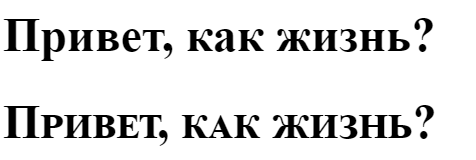
Шрифты
Компьютерный шрифт
Файл шрифта — это файл, содержащий в себе набор символов
и соответствующих им кодов.
Символы могут быть различными по назначению:
Aa
языковые знаки
07
цифровые
☂⁂
графические
$#!
специальные
Вывод шрифтов
Растровые
Векторные
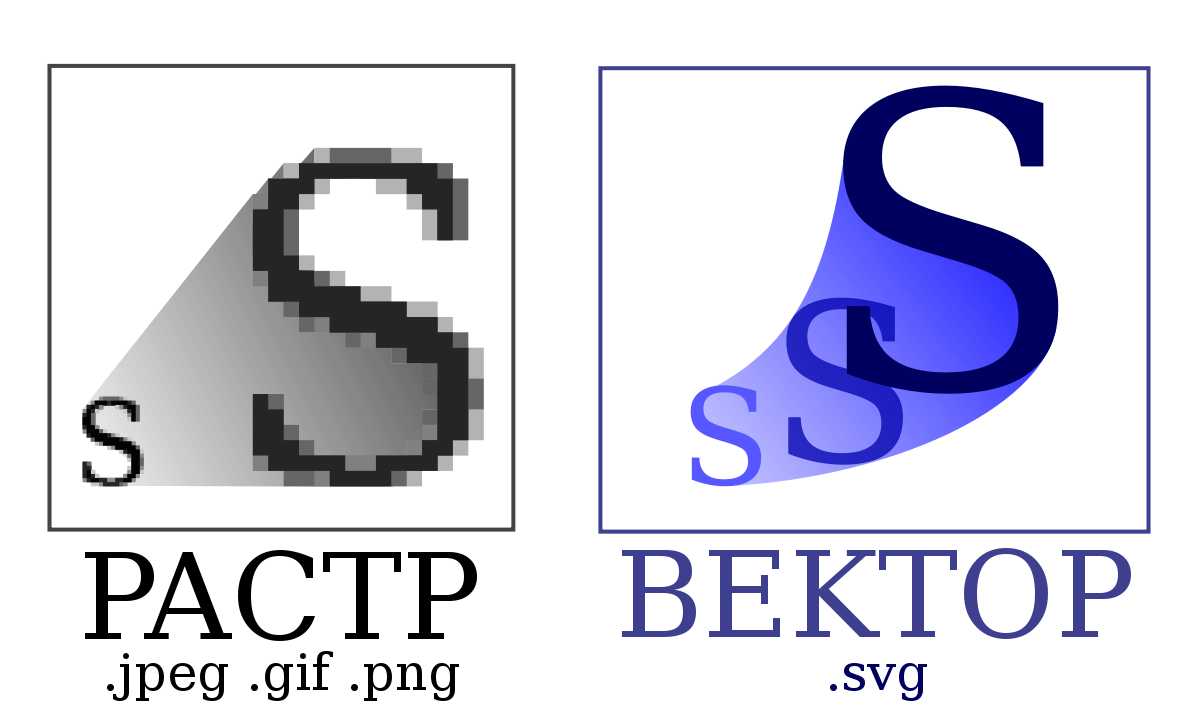
Растровые шрифты
Были распространены в эпоху матричных принтеров и экранов с низким разрешением и представляли собой набор растровых изображений каждого символа в виде битмапа.
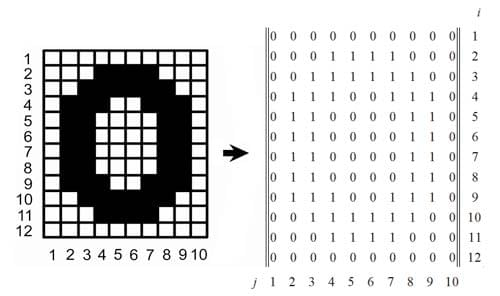
Векторные шрифты
Векторная графика основана на математических формулах геометрических объектов.
Современные шрифты описывают символы с помощью тех самых формул, что позволяет их масштабировать без потери качества, как и любое другое векторное изображение.
Анатомия шрифта
Baseline
Базовая линия — воображаемая прямая линия, проходящая по нижнему краю прямых знаков без учёта свисаний и нижних выносных элементов.
- Высота прописных знаков — расстояние от базовой линии до верхней линии прописных, то есть высота прописных букв без учета свисаний.
- Высота строчных знаков — расстояние от базовой линии до верхней линии строчных, то есть высота строчных букв без свисаний и выносных элементов.
Высота строки — расстояние между базовыми линиями строк.
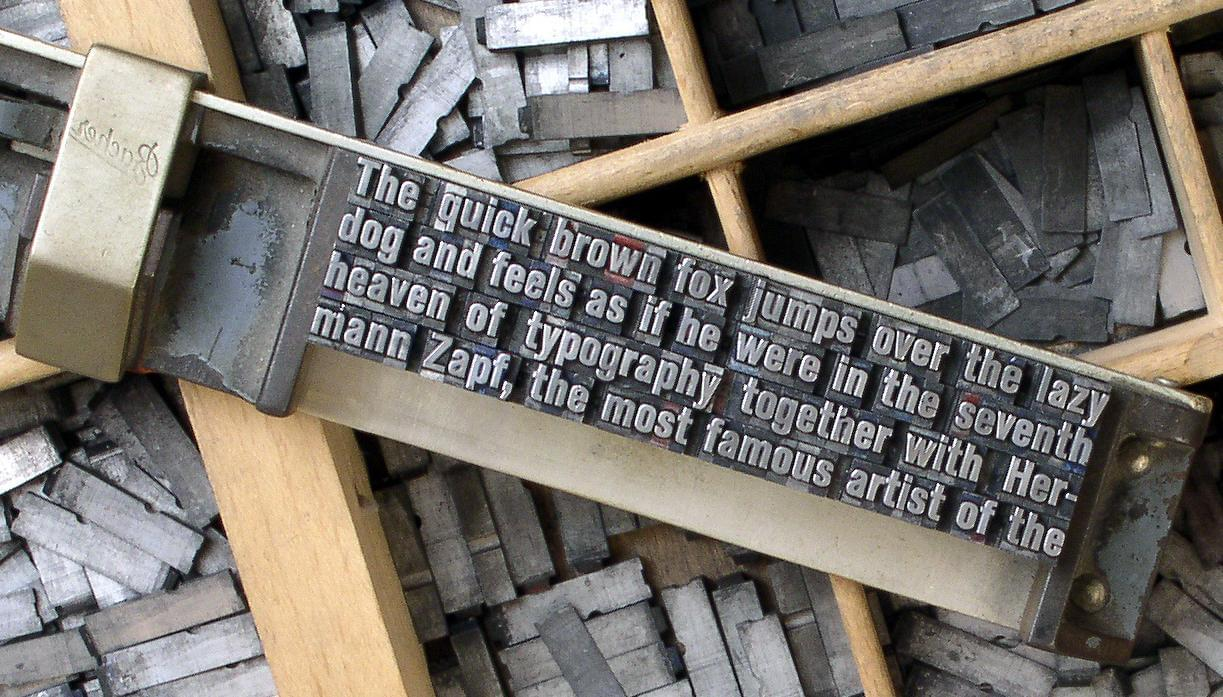
Кегельная площадка — верхняя прямоугольная часть ножки литеры, на которой расположено выпуклое (печатающее) изображение знака.
В цифровом шрифте кегельная площадка важна при проектировании шрифта как прямоугольник, в который вписывается изображение знака.
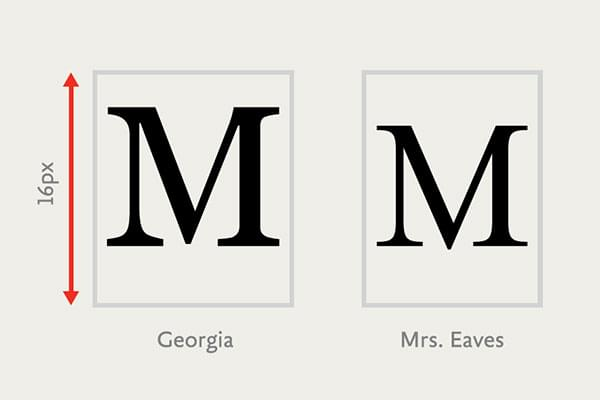
Гарниту́ра в типографике — набор из одного или нескольких шрифтов в одном или нескольких размерах и начертаниях, имеющих стилевое единство рисунка и состоящих из определённого набора типографских знаков.
Размер шрифта
Размер шрифта можно установить с помощью
единиц измерения длины.
С помощью font-size можно определить размер шрифта элемента. Размер шрифта определяется как высота от базовой линии до верхней границы кегельной площадки.
Единицы измерения длины
px — размер шрифта в пикселях.
Так как задание динамического размера требуется нечасто, эта единица измерения является наиболее популярной.
}em или % — размер шрифта в зависимости от размера шрифта родителя. Эти размеры – относительные, они определяются по текущему контексту.
rem(root em) — подобно em наследует значение, но только <html>.
Расстояние между буквами
Для изменения данного расстояния предусмотрено
свойство letter-spacing со значением в любой
единице измерения длины, кроме процентов.
Высота строки
line-height - Высота строки. Устанавливается двумя типами значений: единицами измерения длины или безразмерным множителем.
Расстояние между словами
Для изменения данного расстояния предусмотрено
свойство word-spacing со значением в любой
единице измерения длины, кроме процентов.
Гарниту́ра в типографике — набор из одного или нескольких шрифтов в одном или нескольких размерах и начертаниях, имеющих стилевое единство рисунка и состоящих из определённого набора типографских знаков.
Характеристики рисунка одной гарнитуры:
Наклон
Насыщенность
Плотность
- Начинает загрузку шрифта
- По окончанию загрузки парсит шрифт и применяет к странице
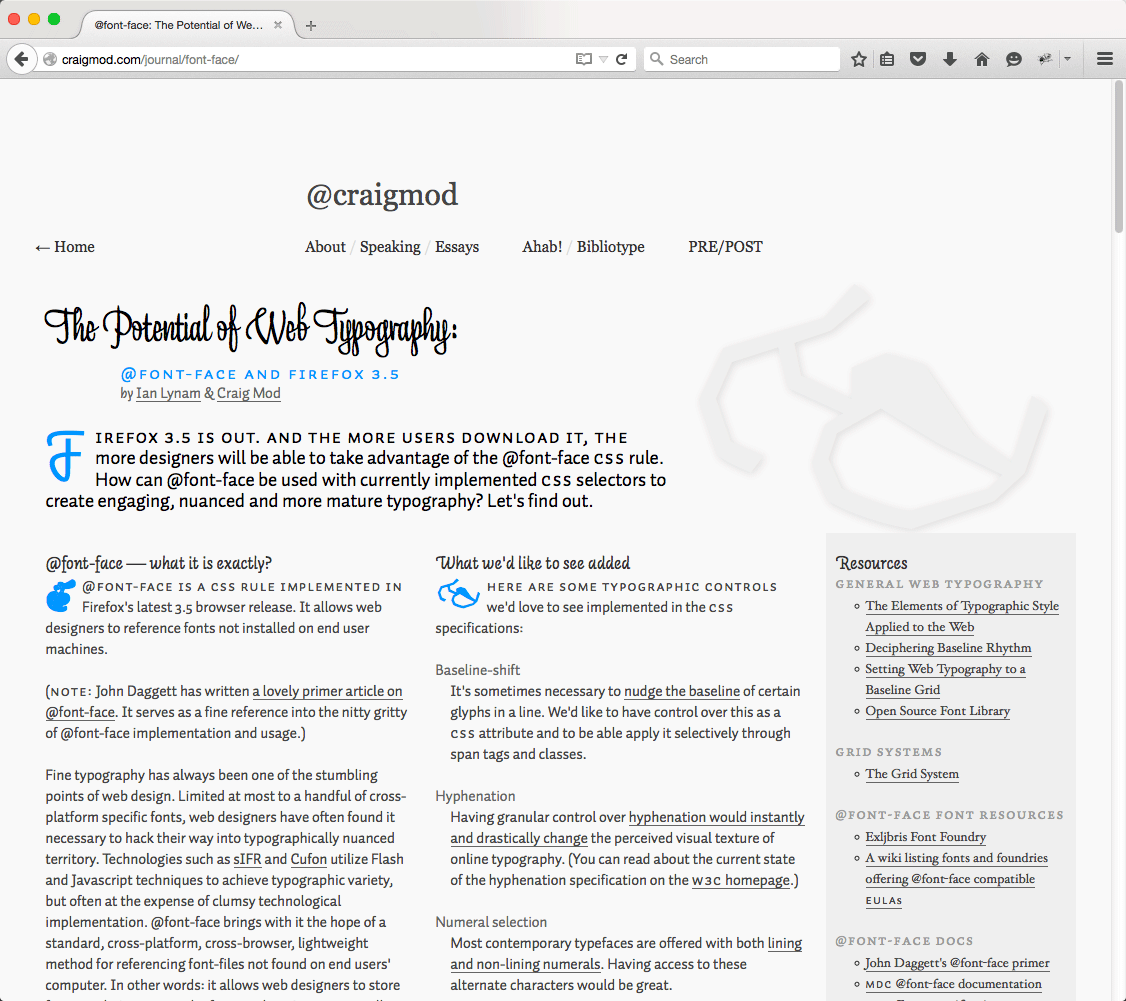
Свойство font